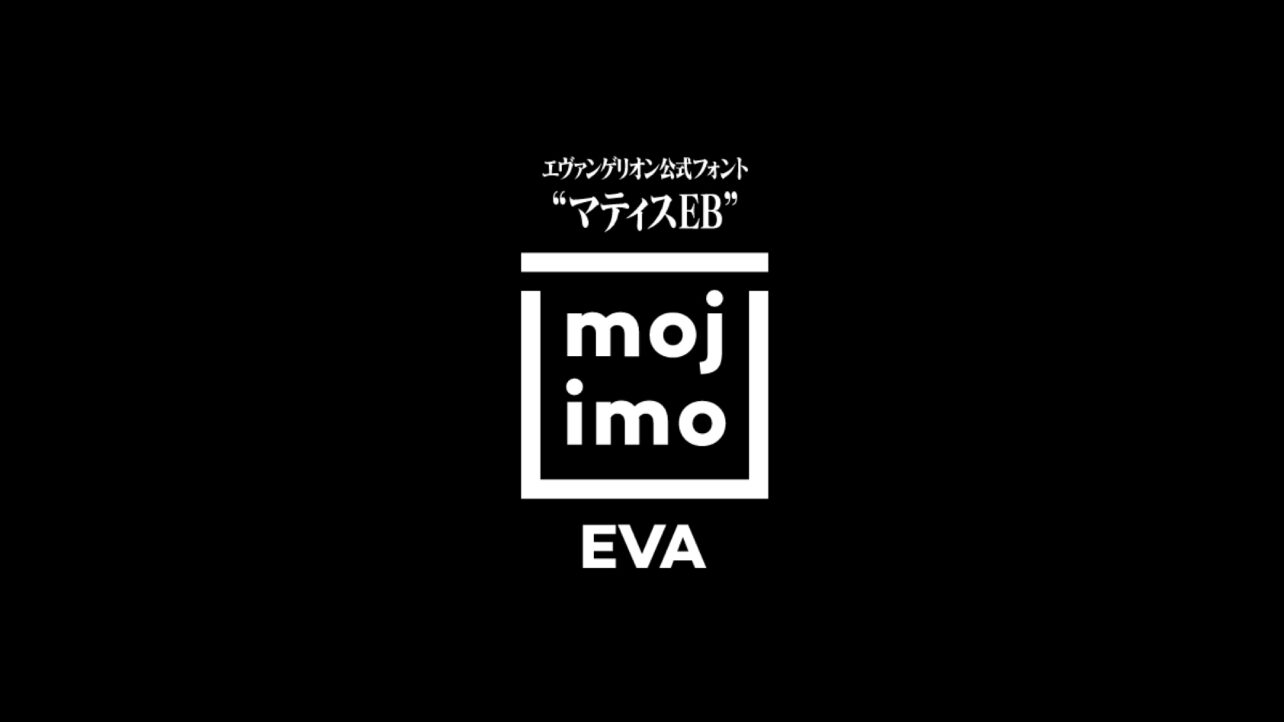
フォントワークス株式会社は、セレクトフォントサービス「mojimo」のパックを販売する。“エヴァフォント”としてもお馴染みの『マティス-EB』書体を「EVA-マティス-クラシック」「EVA-マティス-スタンダード」として収録した、「mojimo-EVA」の提供を開始した。
商品背景
1995年からTV放映を開始した「エヴァンゲリオンシリーズ」。2021年3月には、2007年から始まった映画「エヴァンゲリオンシリーズ」の4部作目を公開し、遂にシリーズの終焉を迎えた。26年間、作品で使われ続けた『マティス-EB』は、後に“エヴァ明朝” や“エヴァフォント”とファンの方々の間で呼んでいただき、今や作品の世界感を想起する重要な存在となっている。ファンの皆さまの盛り上がりを受け、2016年・2020年に『エヴァンゲリオン公式フォント マティスEB TrueType 版』の発売。2020年7月の販売終了後も再販の声が多く、この度「mojimo-EVA」として定額制形式で販売する運びとなった。「mojimo-EVA」にはTVシリーズで使用された「EVA-マティス-クラシック」と、新劇場版で使用された「EVA-マティス-スタンダード」を2書体を収録。マンガ・イラスト・同人誌はもちろん、動画制作にも使用できる。
マティス-EBとは
「マティス-EB」は、フォントワークスのCLASSIC(クラシックシリーズ)の書体。極太の明朝体として1994年にリリースされ、《エヴァフォント》の愛称でも呼ばれるこの書体は、リリース20年を迎えてなお、多くの方々にご使用いただいているフォントワークスを代表する書体のひとつ。たっぷりとした筆と墨を連想させる雄渾な書風で、デジタル時代にあってもエッジの柔らかさとインパクトの強さを兼ね備えている。ウエイト感・重厚感、そして非常に迫力のある極太ウエイトの明朝体として、リリース当初から多くのデザイナーをはじめ、印刷会社や製版会社、そして出力センターなどで、いわゆる印刷用フォントとしてご導入いただいた。